이 글에서는 글씨체 찾기와 한글 글씨체 찾기 방법을 소개하며, 다양한 예쁜 폰트를 검색하고 다운로드하는 간단하고 효과적인 절차를 안내합니다.
글씨체 찾기 첫걸음
글씨체 찾기는 많은 크리에이터와 디자이너에게 중요한 작업입니다. 대부분의 사람들은 좋은 글씨체를 사용하여 작품의 품격을 높이기 원하죠. 하지만 적절한 폰트를 정확히 선택하는 것은 생각보다 어려울 수 있습니다. 글씨체 찾기의 첫 단계는 당신이 원하는 스타일을 아는 것입니다. 예를 들어, 현대적이고 깔끔한 디자인을 원한다면 세리프 글씨체보다는 산세리프 글씨체를 고려하는 것이 좋습니다. 글씨체란 단순한 문자 형태가 아니라, 그 자체로 감정을 전달할 수 있는 매체라는 사실을 잊지 않아야 합니다. 이렇게 스타일을 정리하고 나면 선택할 수 있는 범위가 줄어들어, 원하는 글씨체를 찾는 과정이 좀 더 수월해집니다.
그리고 여러분이 찾는 글씨체의 특성을 생각해 보세요. 예를 들어, 손글씨 느낌이거나, 둘레가 부드러운 디자인이 필요할까요? 각 글씨체마다 독특한 개성과 특성이 있습니다. 여러 웹사이트에서 한글 글씨체 찾기 전용 필터를 통해 원하는 스타일을 좁힐 수 있습니다. 이처럼 원하는 스타일과 특성을 정리하면, 여러분만의 멋진 폰트를 찾는 여정이 훨씬 흥미로워질 것입니다.
여러분이 필요한 글씨체에 대해 다양한 아이디어를 떠올리고 나면, 이제 본격적으로 서핑을 시작할 차례입니다. 수많은 폰트 제공 사이트들이 있으며, 이곳에서 사용자 리뷰와 평점을 활용할 수도 있습니다. 또, 여러 플랫폼에서는 무료 또는 유료로 제공되는 글씨체를 찾을 수 있으니 소중한 시간을 절약할 수 있는 방법이기도 하죠. 하지만 주의할 점은 상업적 사용에 대한 라이선스 조건을 꼭 확인해야 한다는 것입니다.
초보자라면 첫 시도에서 모든 것을 완벽하게 하고 싶어하겠지만, 새로운 글씨체를 고르는 것은 과정입니다. 다양한 사이트를 탐색해 보고 여러 글씨체를 다운로드해 보세요. 그런 다음 각 폰트를 시각적으로 조합해 보면서, 자신의 목소리가 잘 드러나는 스타일을 익혀가는 것이죠. 여러분의 디자인이 더욱 빛날 폰트를 찾아가는 놀라운 여정, 한 걸음씩 나아가 소중한 시간을 보내보세요.
폰트 검색 사이트 활용하기
얼마나 많은 글씨체가 존재할까요? 이 질문은 모든 디자이너가 한 번쯤은 해봤을 것입니다. 다양한 글씨체 찾기 플랫폼에서 원하는 스타일을 직접 탐색할 수 있습니다. 예를 들어, ‘Google Fonts’는 무료로 사용할 수 있으며, 다양한 스타일을 제공하죠. 또한, 한글 글씨체 찾기에서 크게 발전한 ‘자작 폰트’도 좋은 대안입니다. 자신의 손글씨를 그대로 적용하여 유일무이한 폰트를 만들어주세요.
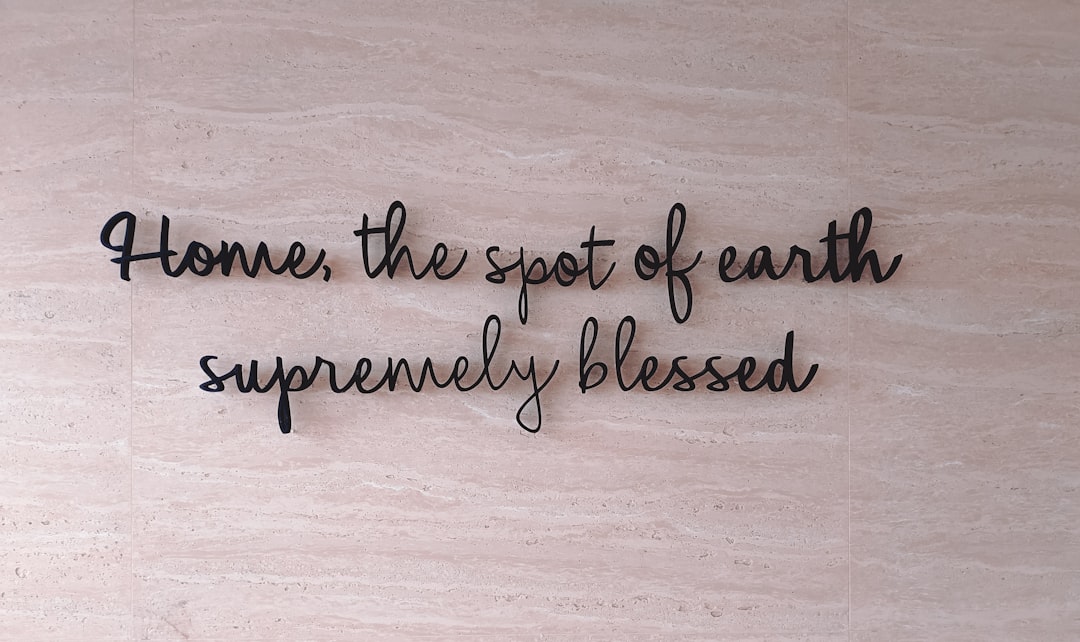
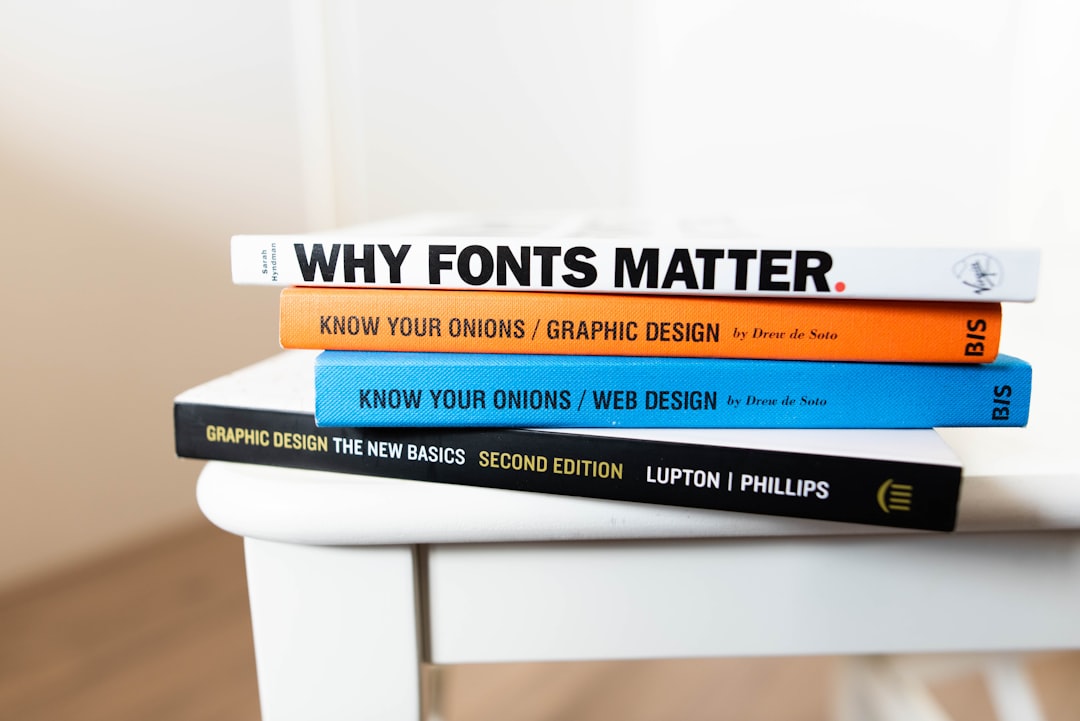
또한, 유료 글씨체를 제공하는 사이트도 많이 있습니다. ‘MyFonts’나 ‘FontShop’과 같은 사이트는 사용자가 원하는 스타일과 기능성, 접근성을 바탕으로 폰트를 검색할 수 있게 도와줍니다. 유료 폰트는 품질이 뛰어나며, 저작권 문제에 대한 걱정 없이 자유롭게 사용할 수 있습니다. 다만 처음에는 시도해보고 싶은 몇 가지 무료 글씨체를 사용해 보는 것을 추천합니다.
이런 사이트들을 탐색하면서 발견한 마음에 드는 글씨체는 꼭 목적으로 사용해보세요. 텍스트를 작성해볼 때, 그 폰트가 과연 자신의 감정과 잘 연결될 수 있을지 생각하면서 디자인을 시작해보는 것이죠. 기본적인 아이디어부터 시작해 여러 스타일을 비교하며, 적절한 폰트를 선택해나가는 과정은 글씨체를 찾는 기쁨을 배가할 것입니다.
각 사이트에서 제공하는 다양한 필터와 기능을 적극 활용해보세요. 크기나 굵기에 따라 글씨체를 정렬하거나, 특정 카테고리의 글씨체만을 선택할 수 있습니다. 이러한 활동들은 여러분의 디자인 감각을 넓히고, 더 많은 글씨체를 접할 기회를 제공합니다. 글씨체 찾기 여정의 끝은 언제나 흥미로워요. 그러니 지루해하지 말고 계속해서 다양한 폰트를 탐색해보세요.
사용하면서 느낀 점을 정리해보는 것도 좋은 방법입니다. 선정한 폰트가 글의 흐름을 어떻게 변화시켰는지, 감정적으로나 시각적으로 어떤 느낌을 주었는지에 대해 작성해보세요. 모든 사용 경험은 다음번 글씨체를 찾을 때 큰 도움이 될 것입니다. 올바른 글씨체를 찾는 여정은 계속됩니다! 어떤 글씨체가 나올지 기대해 보시죠!
여러분만의 글씨체 활용하기
모든 과정을 마치고 나면, 이제 원하는 글씨체를 활용할 수 있게 됩니다. 어떤 폰트를 사용하든 간에 여러분의 디자인이나 프로젝트에 생명을 불어넣는 데 큰 역할을 할 것입니다. 독창적인 글씨체를 사용함으로써 작품의 아이덴티티를 새롭게 하고 감정을 더욱 세심하게 전달할 수 있게 되는 것이죠. 글씨체 찾기와 활용까지 여러분이 원하는 목표에 맞게 조정하는 것이 중요합니다.
그렇다면, 어떤 방식으로 글씨체를 활용할 수 있을까요? 다양한 플랫폼에서 새로운 폰트를 적용해보며 시도를 거듭해보세요. 당신의 웹사이트 블로그, SNS 게시물, 포스터나 브로셔 디자인 등 모든 곳에 이 글씨체를 넣어보는 겁니다. 여러 가지 조합을 통해 이전에는 예상치 못했던 놀라운 디자인이 탄생할 수 있습니다.
여러분의 목소리가 글씨체를 통해 더욱 부각될 수 있으며, 디자인에도 생동감이 더해지지요. 중요한 것은, 자신만의 개성을 살려 디자인을 해보는 것입니다. 폰트의 선택과 사용은 단순히 글자의 형태가 아니라, 여러분의 아이디어와 감정을 표현하는 수단이기 때문입니다. 그러므로 다양한 시도를 통해 글씨체를 활용하는 즐거움을 만끽하세요.
검색하고 다운로드한 폰트는 이제 당신의 창작물에서 단단한 기반이 되어 줄 것입니다. 글씨체는 단순한 도구일 뿐만 아니라, 여러분의 브랜딩과 이미지에 큰 변화를 가져오는 중요한 요소입니다. 글씨체 찾기를 통해 얻은 경험이 여러분의 작업에 더 커다란 서사를 담길 수 있도록, 계속하여 다양한 글씨체를 탐색하는 여정을 이어가길 바랍니다!
덧붙이는 글: 폰트 선택에서 기억해야 할 점
| 필터 옵션 | 설명 |
|---|---|
| 스타일 | 세리프, 산세리프, 슬랩세리프 등 |
| 무게 | 라이트, 레귤러, 볼드 등 |
| 용도 | 본문, 제목, 광고 등 |
이 표는 다양한 필터 옵션을 이용해 한글 글씨체 찾기를 좀 더 수월하게 할 수 있도록 도와줍니다. 여러분이 원하는 글씨체를 더욱 쉽게 찾을 수 있는 모든 팁과 도구를 활용해 보세요! 과연 어떤 퍼즐이 여러분을 기다리고 있을까요?